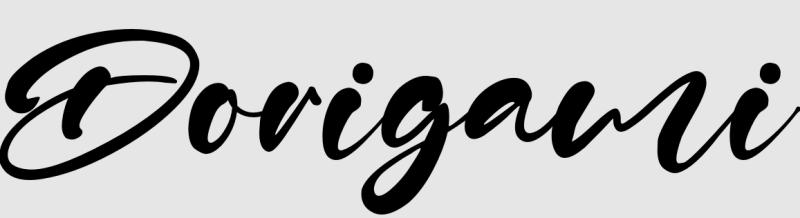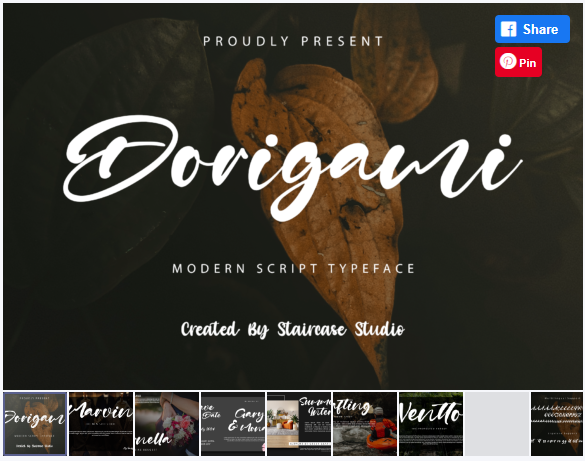
Dorigami - это современный шрифт, в котором собраны буквы и цифры, подходящие для любых ваших творческих проектов. Он отлично подходит для логотипов, брендинга, цифровых надписей, дизайна футболок и одежды, плакатов, журналов, вывесок, рекламы и многого другого!